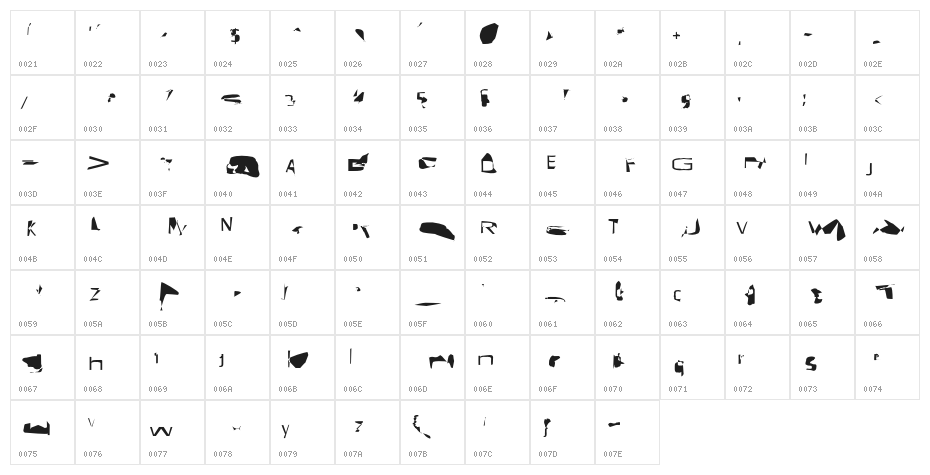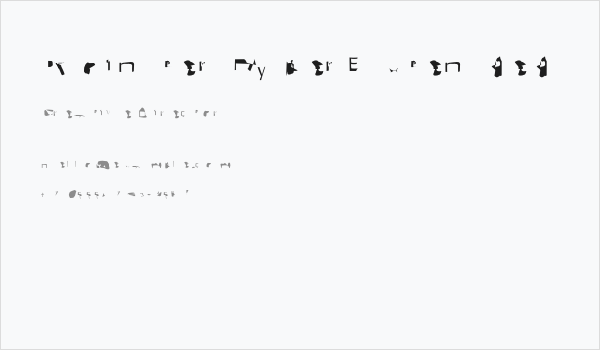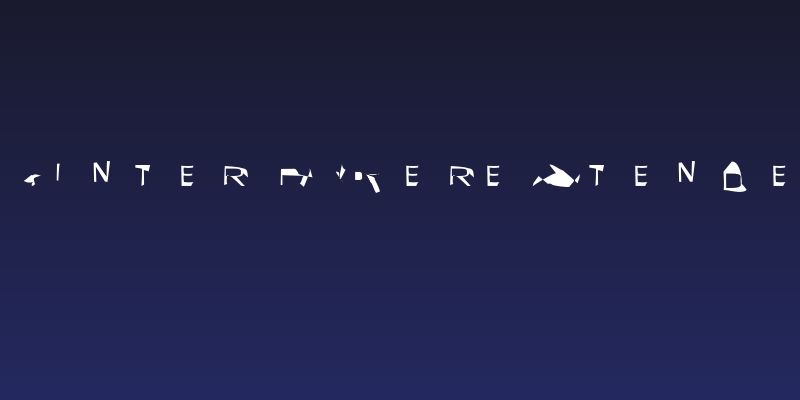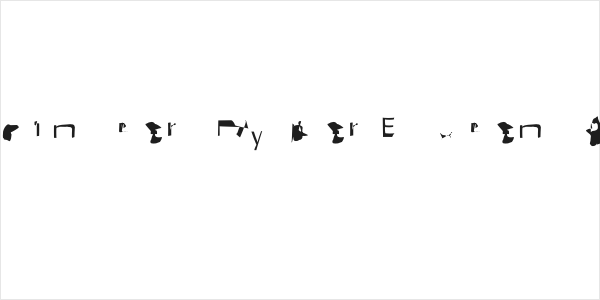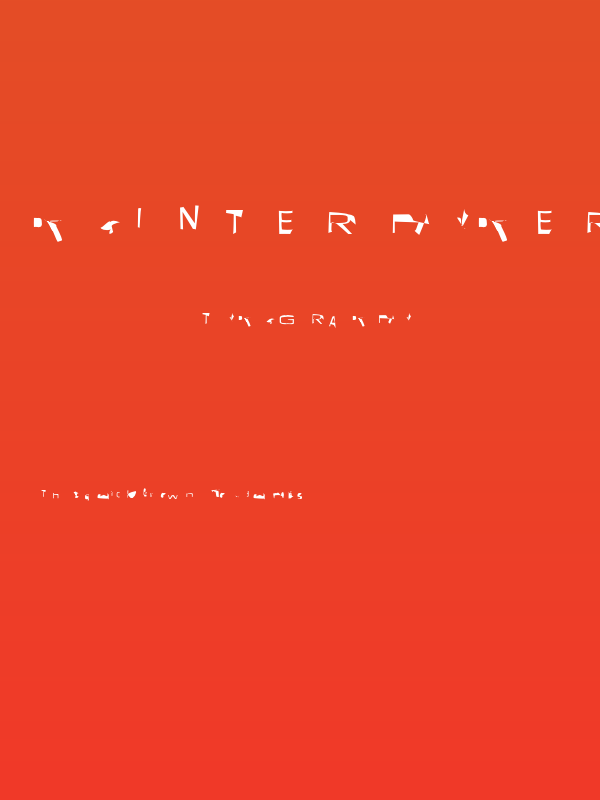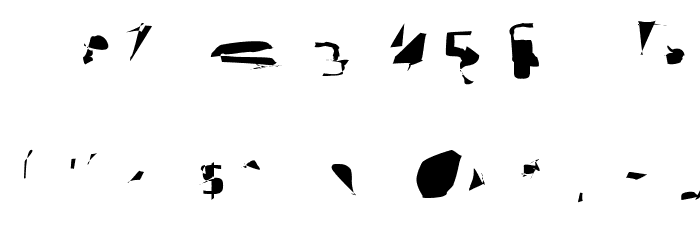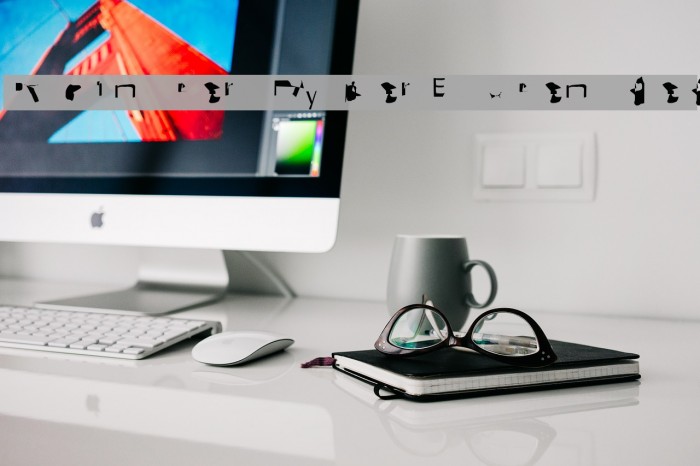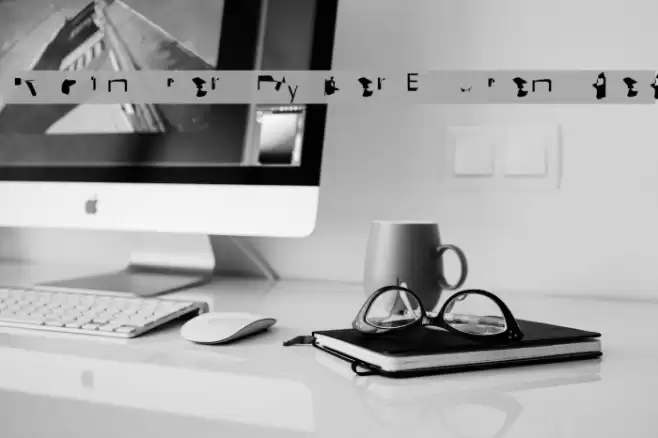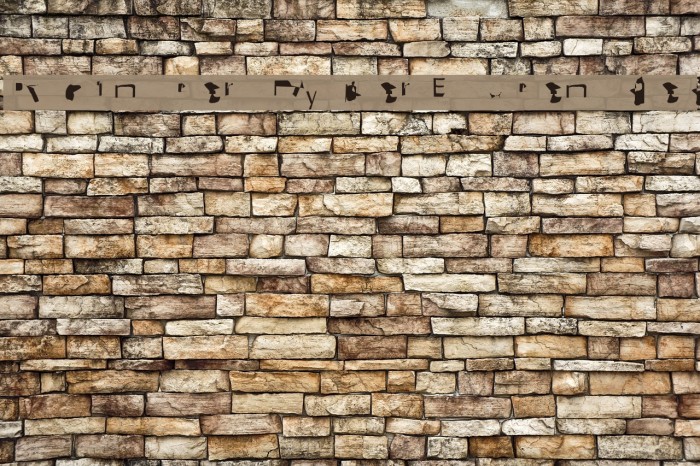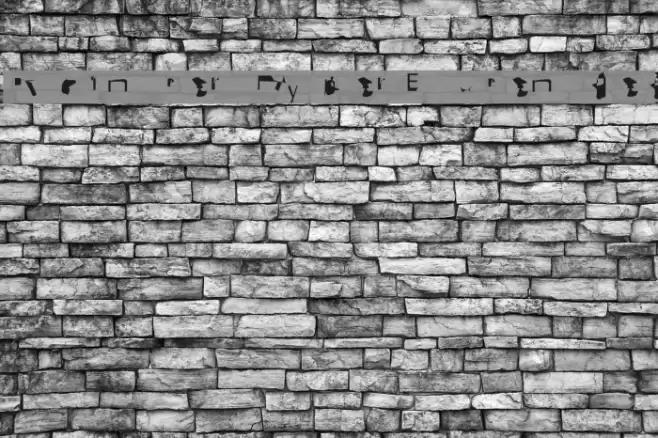
Pointer HyperExtended Font
✎ Distorted Eroded
| Категория | Distorted Eroded |
| Общий стиль | Modern, Experimental |
| Область применения | Logos, Headlines, Artistic projects |
| Рекомендуемые проекты | Ideal for experimental art projects, edgy branding, album covers, and posters that require a striking and unconventional typeface. |
Pointer HyperExtended
| Автор | Fonts by Dieter Steffmann |